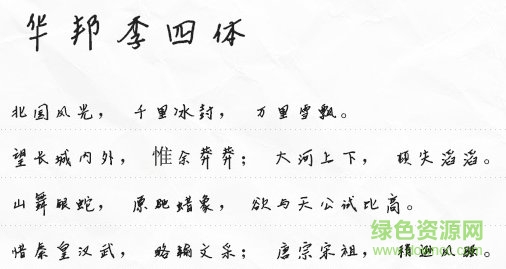
華邦李四體是華邦字體官方推出的一款造型別致的中文手寫(xiě)體,結(jié)構(gòu)上不拘泥一格,中文字跡隨意灑脫,中文書(shū)寫(xiě)流暢簡(jiǎn)介,給人十分工整大方的視覺(jué)體驗(yàn),喜歡的朋友就來(lái)綠色資源網(wǎng)試試吧!
華邦李四體字體是一款適合手寫(xiě)藝術(shù)設(shè)計(jì)的字體,造型上十分簡(jiǎn)約隨和,結(jié)構(gòu)上打破常規(guī),兼具手寫(xiě)字體和pop字體的庚哥特色,讓藝術(shù)設(shè)計(jì)更加出彩。